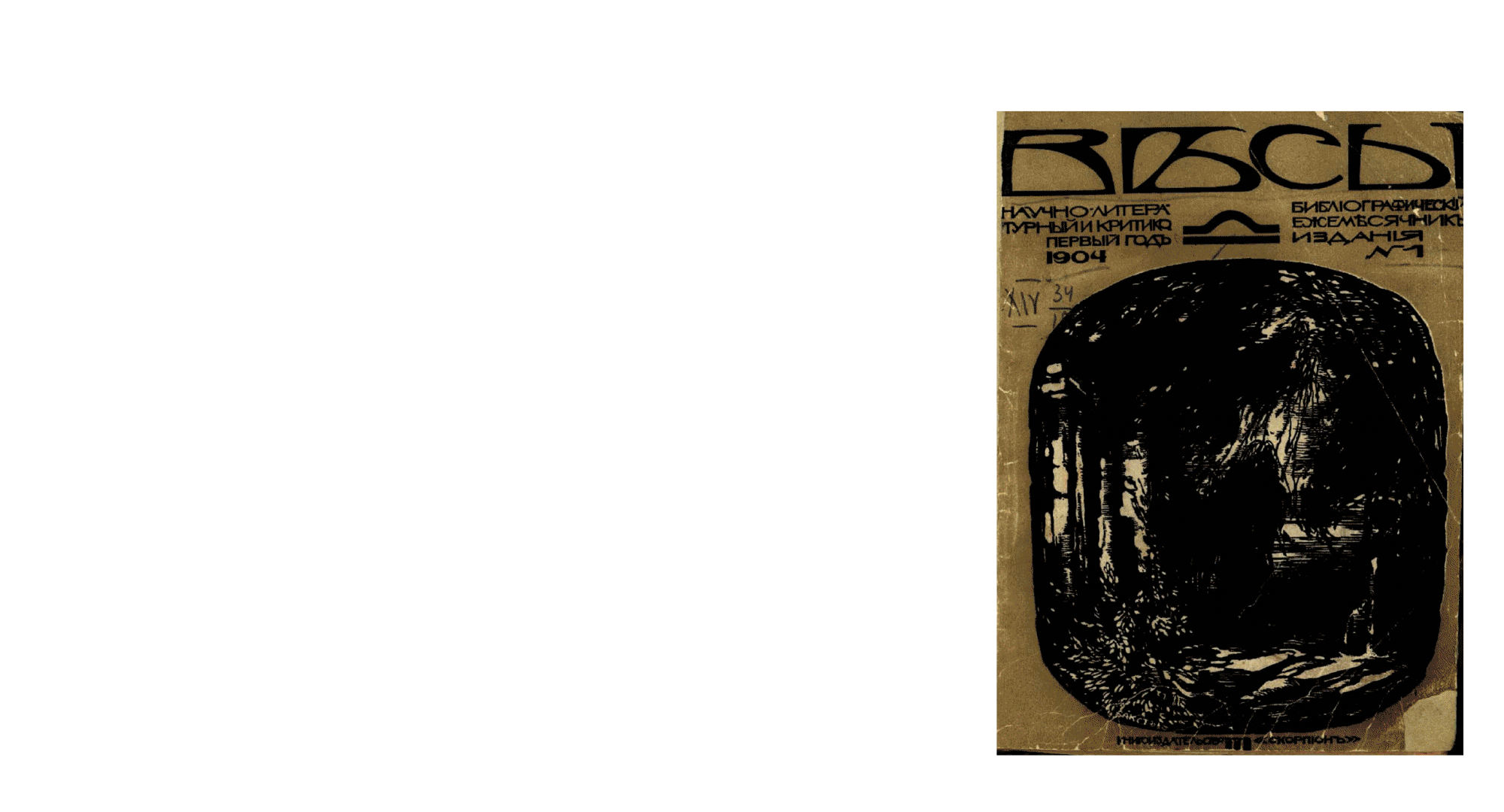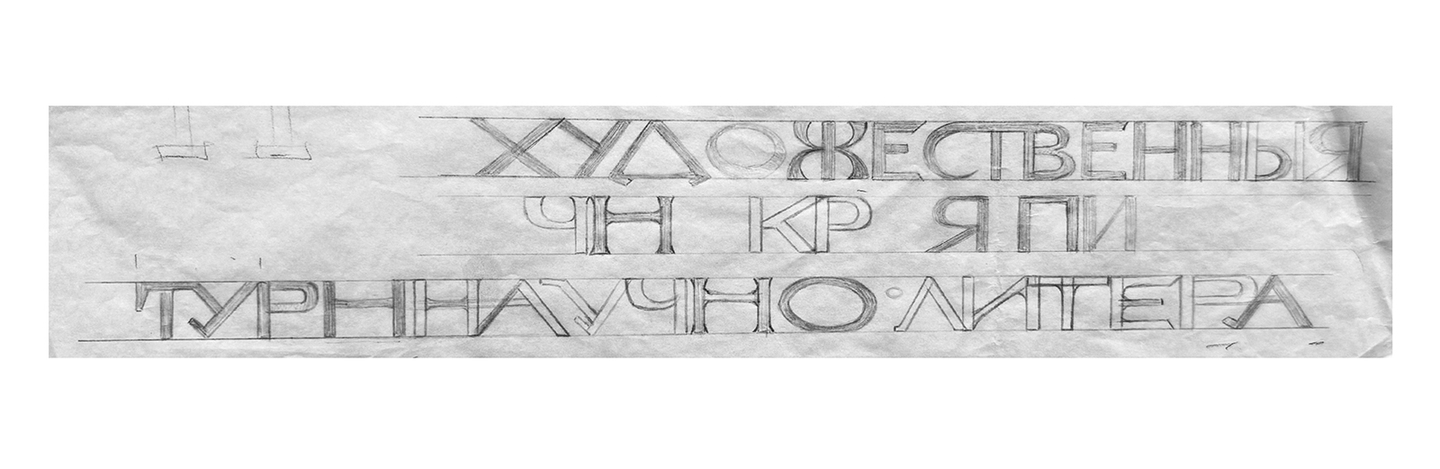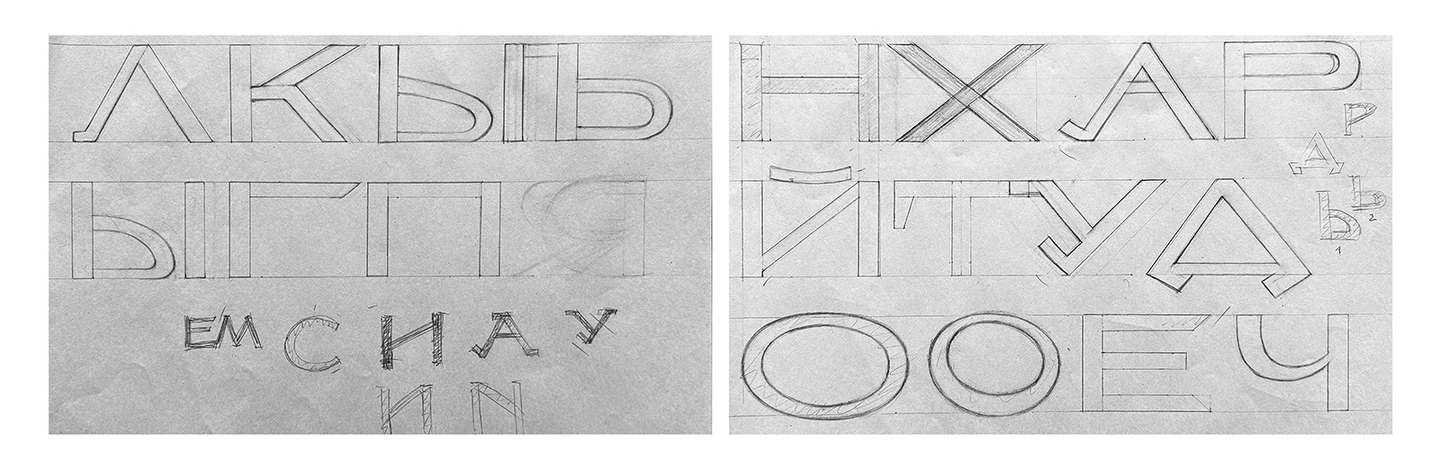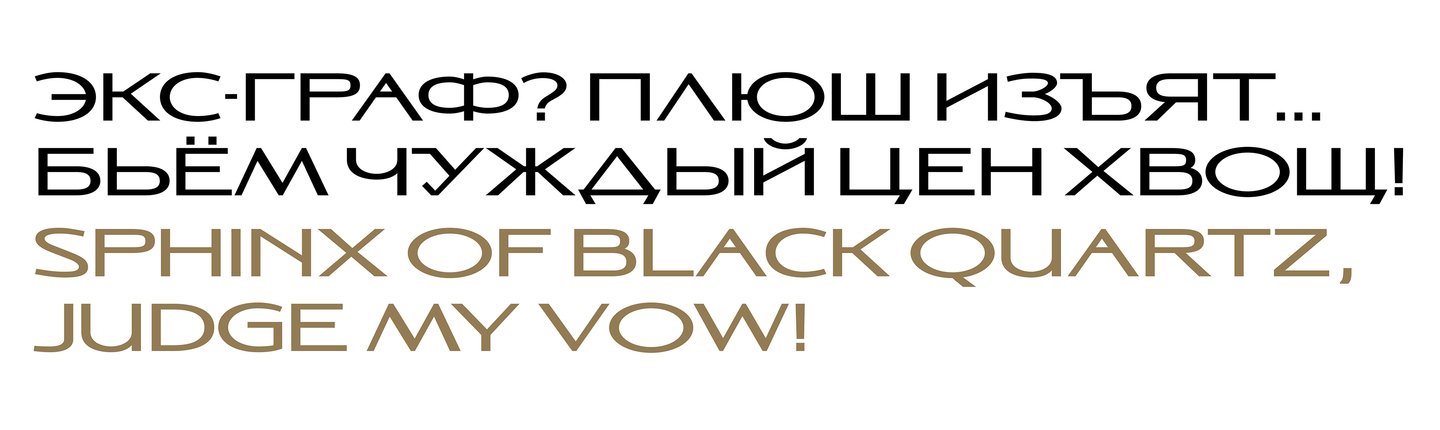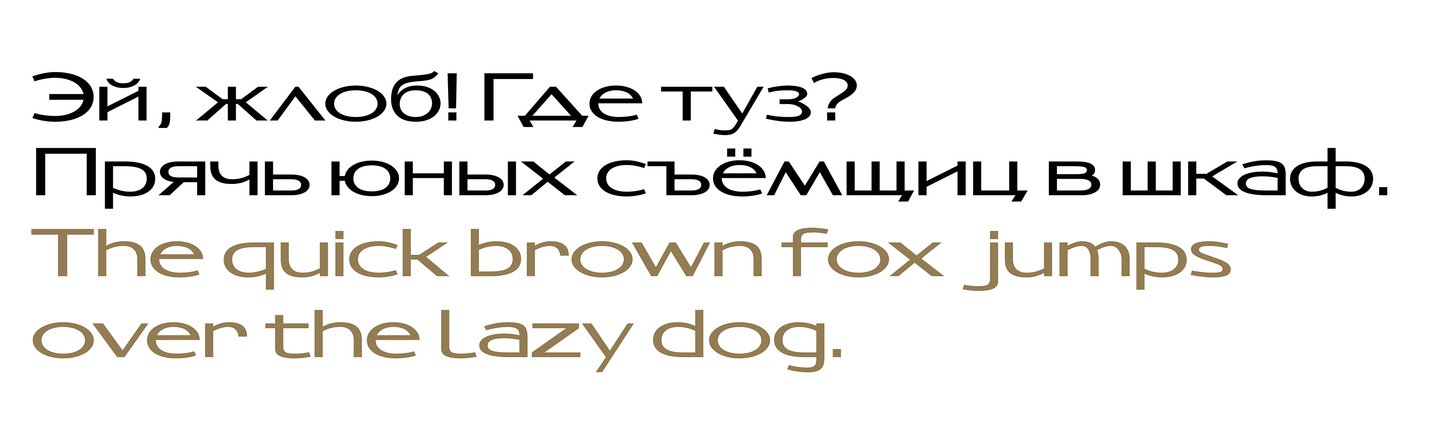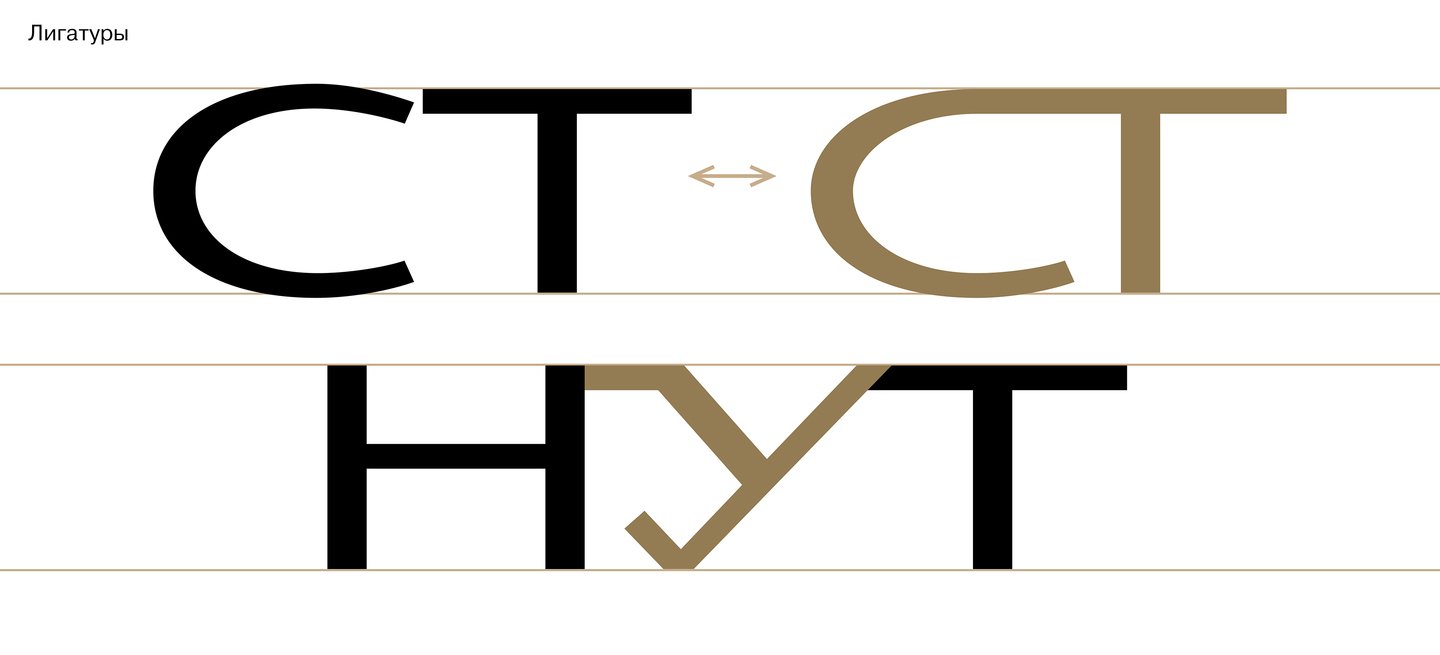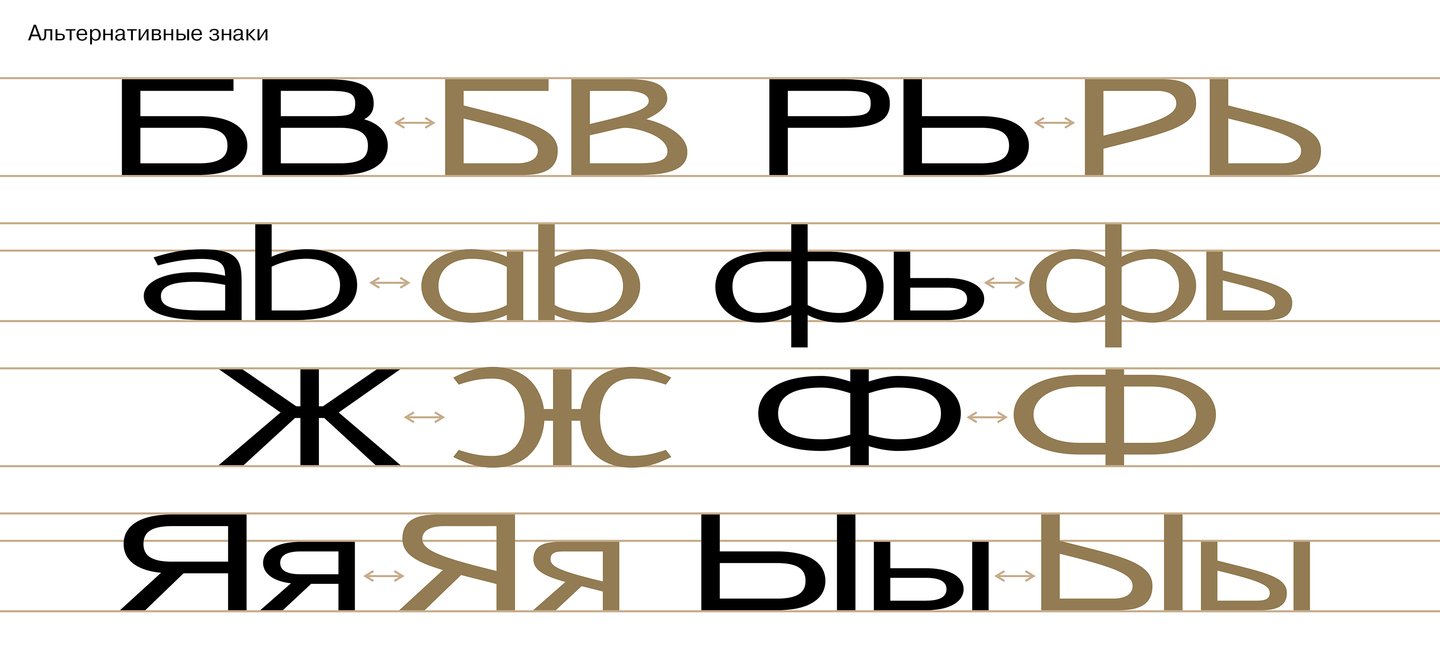
Проект шрифта на основе обложки журнала «Весы», сделанной по эскизу Л. Бакста.
Гарнитура «Бакст» родилась из обложки журнала
«Весы» 1904 года, выполненной по эскизу Бакста.
Ежемесячник был не просто литературно-художественным журналом, а частью культурной среды — эпохи, в которой художник стремился объединить литературу, графику, театр, архитектуру и декоративное искусство в единый образ.
Особый интерес представляет даже не столько декоративное решение обложки в целом, сколько сама надпись: её пластика, пропорции, ритм
и вытянутость. Яркая по своей выразительности, плотности набора и брутальности форм она сразу зацепила мое внимание.
Интерес подкреплялся еще и личным вызовом: получится ли из столь емкой фразы полноценная шрифтовая гарнитура?
Было разработано брусковое начертание, так как в оригинальной исторической надписи засечки у некоторых знаков очевидно использовались лишь для заполнения пространства между буквами.
Такое решение продолжает и усиливает приём, к которому обращался Бакст в оригинале: засечки помогают активнее заполнять межбуквенные пустоты, лучше удерживать строку и делать набор более цельным и собранным.
Узкое начертание родилось из анализа ширин знаков в историческом оригинале. Там буквы
в рамках одного варьируются по ширинам.
Это подтолкнуло к созданию более узких знаков, ведь исходный гротеск довольно широкий.
В процессе работы было также замечено, что
в историческом оригинале иногда контраст
в знаках варьируется, поэтому следующим начертанием стал контрастный шрифт.
Шрифт стал более утонченным, при этом не потеряв ни своего характера, ни брутальности.
После этого показалось логичным сделать контрастный шрифт с засечками, чтобы максимально расширить шрифтовую систему
и показать, что гарнитуру можно развивать
по разным осям.
Такое начертание объединило в себе два ранее найденных направления — брусковую устойчивость и более утончённую контрастную пластику.
В каждом начертании полный комплект латинских знаков, расширенный набор кириллических знаков, служебных и диакртических знаков, альтернативных букв и лигатур.